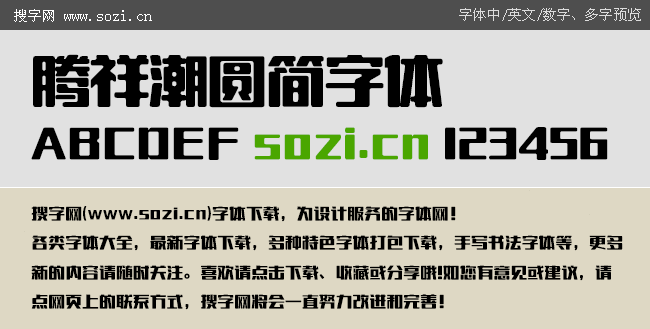
騰祥潮圓簡字體
搜字網提供一款騰祥潮圓簡中文藝術字體下載,潮圓是一款富于變化的美術類黑體,是在潮黑的基礎上變換設計而成。雖然字形結構與潮黑相同,但兩款字的風格氣質截然不同。潮圓將潮黑的棱角柔化形成被融化之感,融化了的筆畫圓潤富于親和力。字形結構扁方、端莊,橫豎筆畫粗細比例適度、豎筆粗壯有力,布白均勻、行文貫通。潮圓筆畫簡潔圓潤細微處變換靈動,即實用又富有裝飾效果。適合標題用字,可用于印刷出版、包裝設計、廣告設計、網頁設計等。